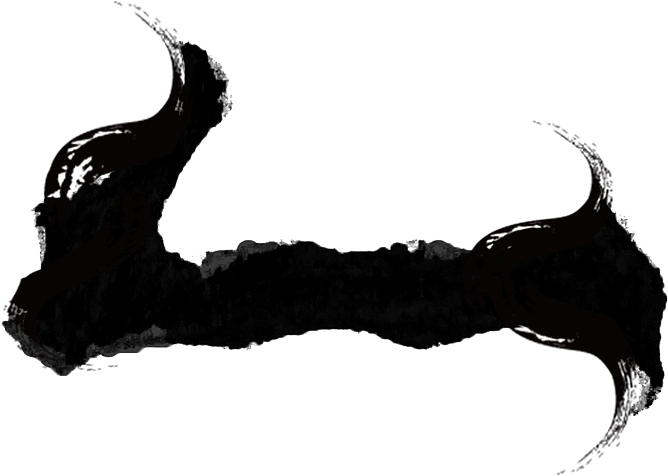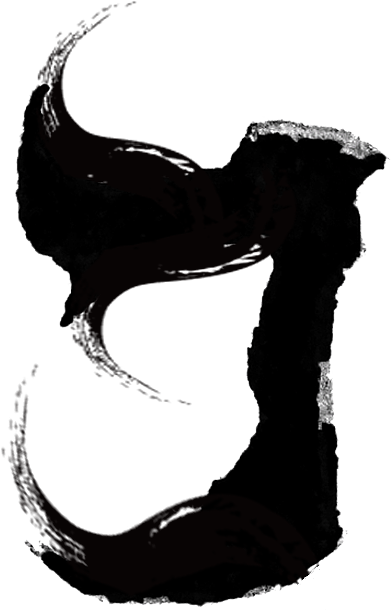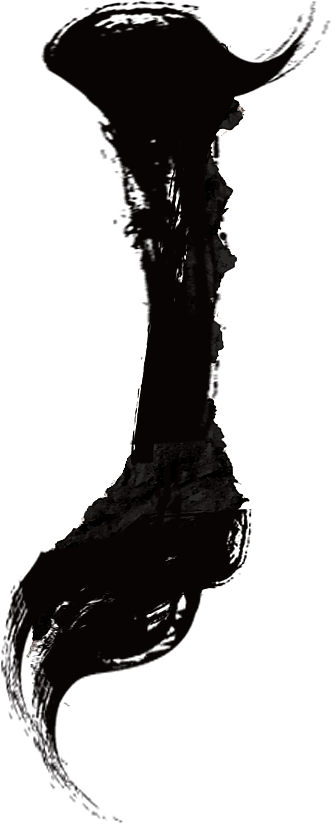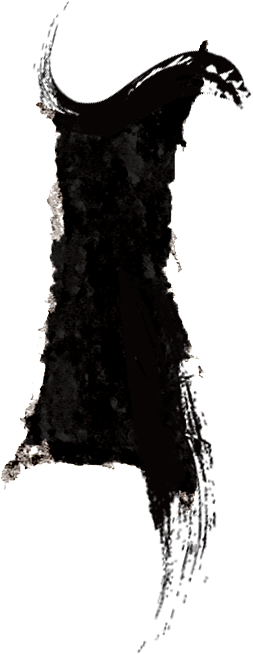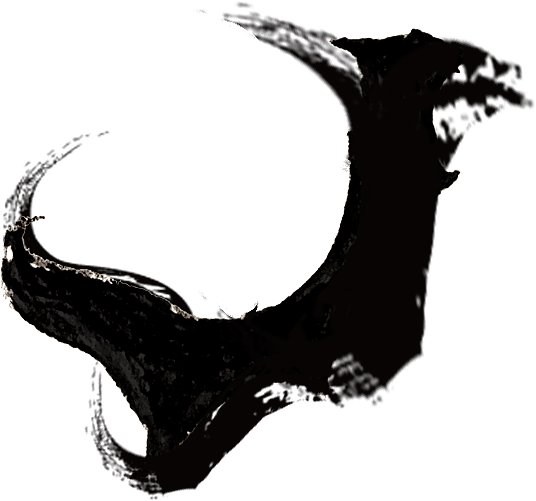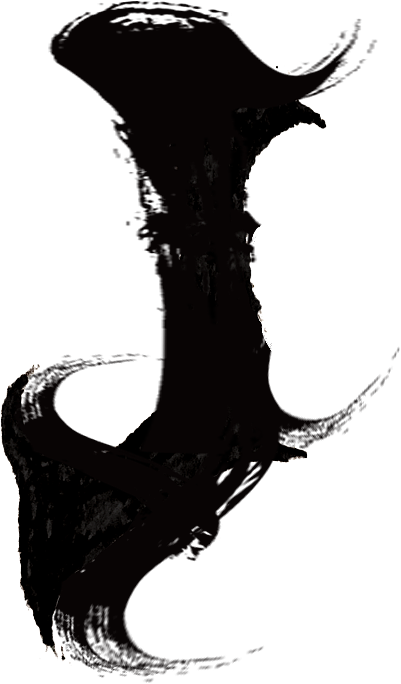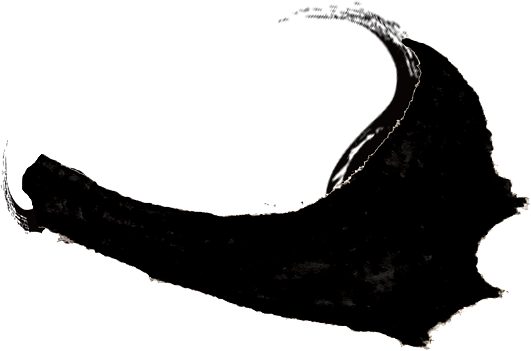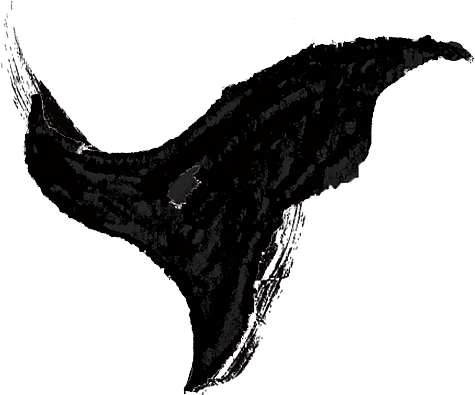
云墨北原创设计笔触
云墨北
云墨北原创设计笔触,细琢字形,采用宣纸手绘后电子录入调色,再使用笔刷美化细节。声明:在未获得授权前禁止二改商用,关注云墨北(sharecho)微信公众号后发送消息“获取笔触授权”可免费获取商业授权,并获得psd源文件,获取商业使用后的源文件仅限个人使用,禁止共享或二次销售。